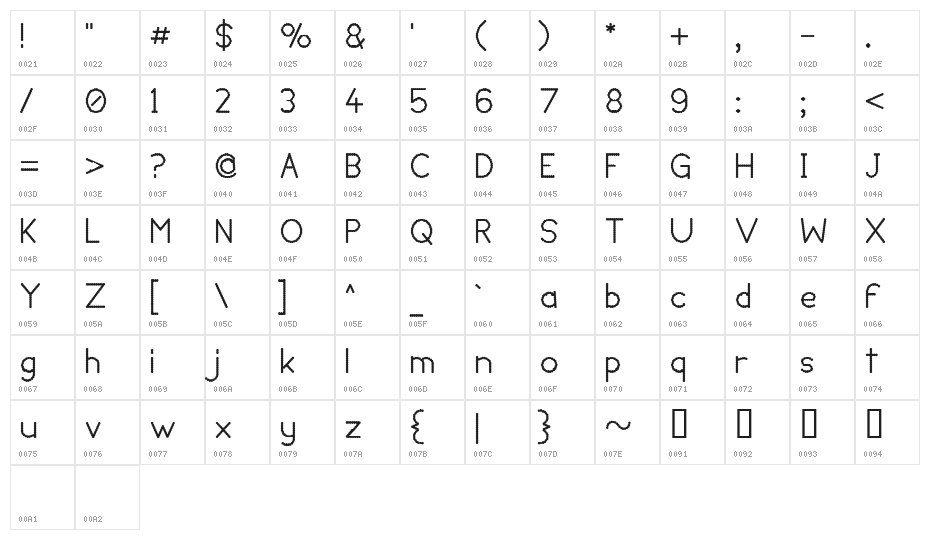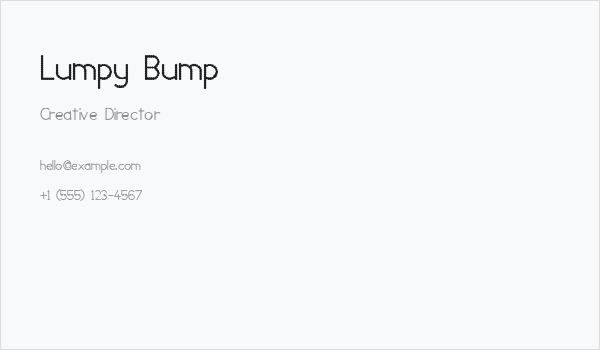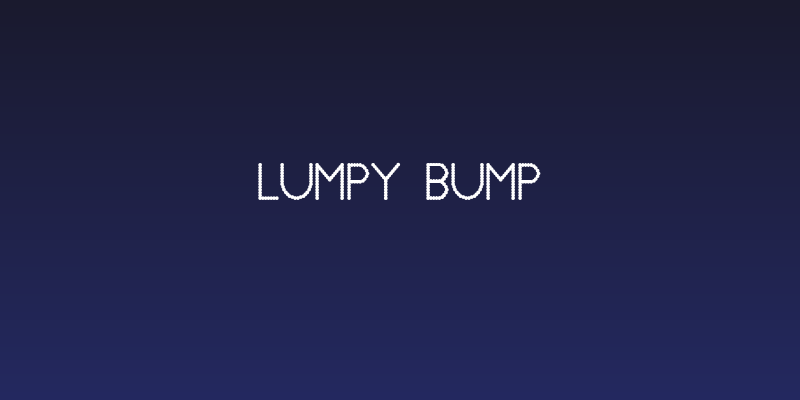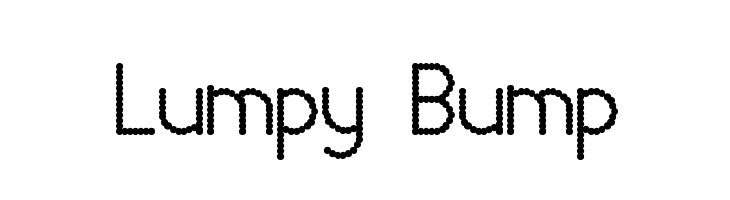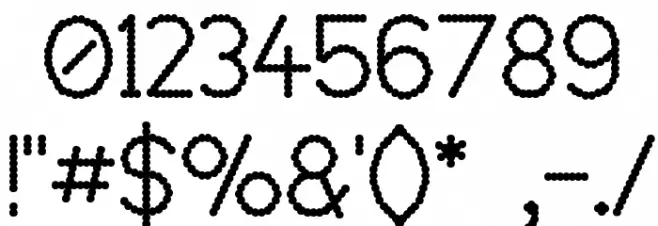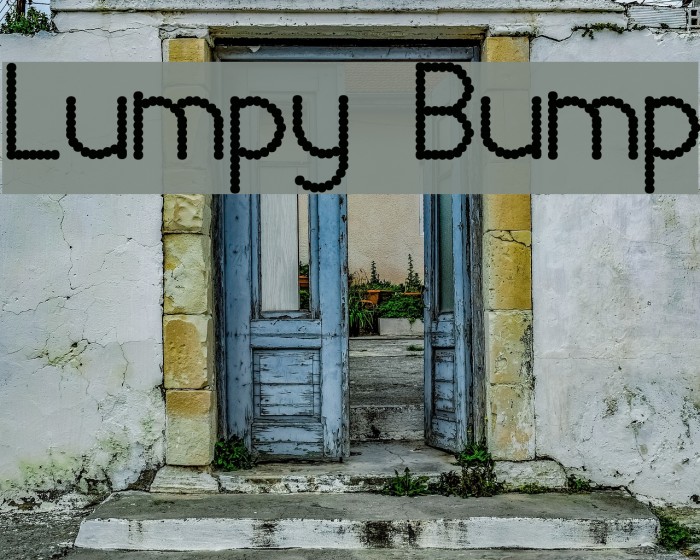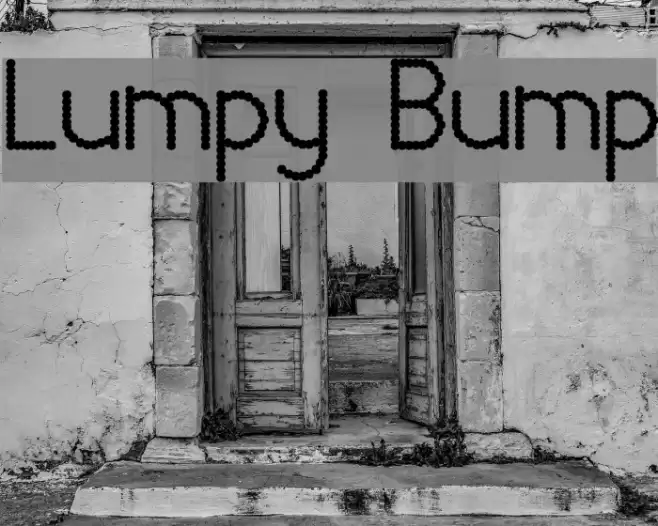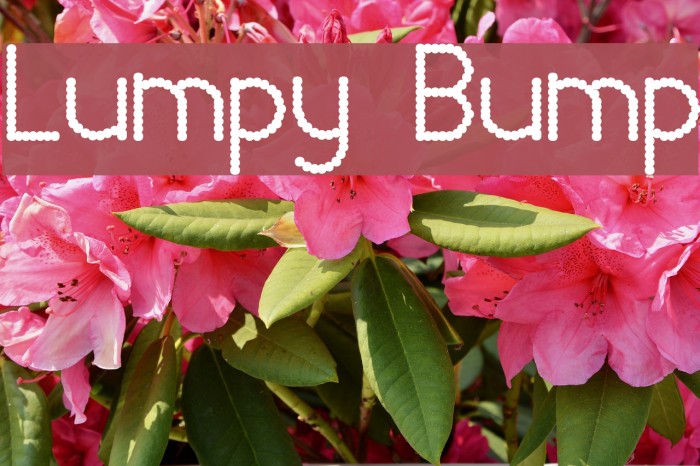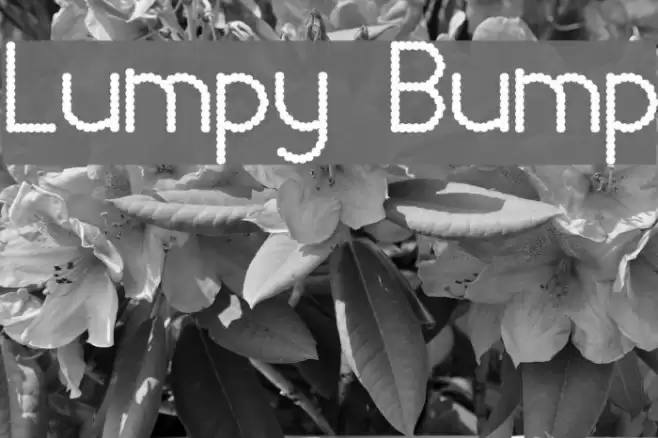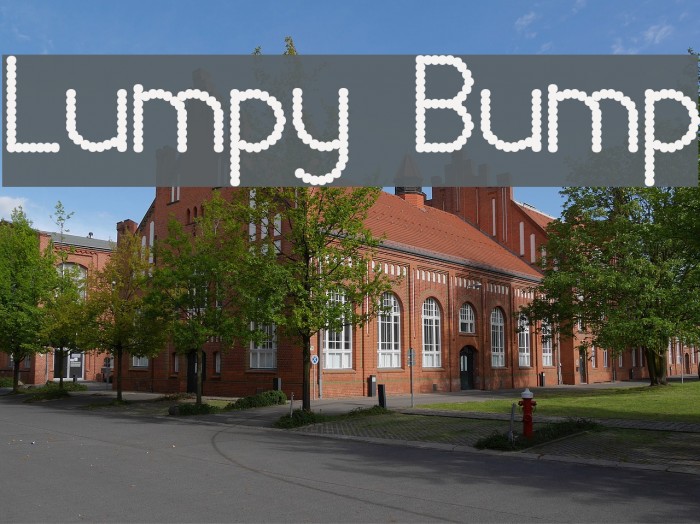
Lumpy Bump Font
| Gesamtstil | Playful |
| Anwendungsfall | Headlines, Logos, Creative projects |
| Vorgeschlagene Projekte | Ideal for children's books, playful branding, party invitations, and creative posters. |